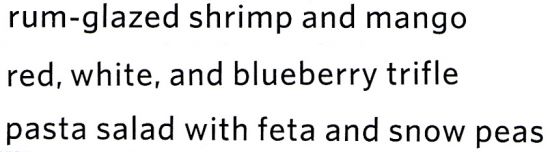
Wer kennt diese Schriftart ?
wer kann mir den namen der beigefügten schriftart nennen ? ich bin leider nicht fündig geworden. bin dankbar für jeden hinweis.
ja, "a" und "d" ganz leicht abgerundet.